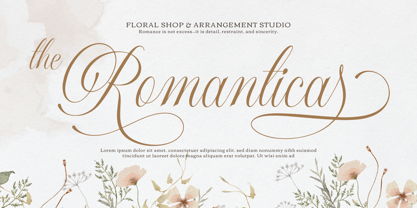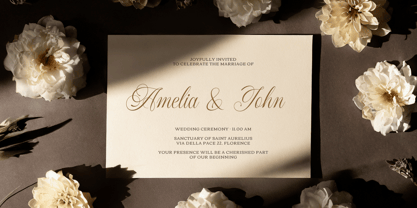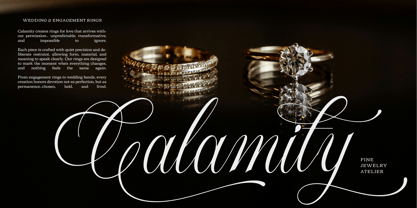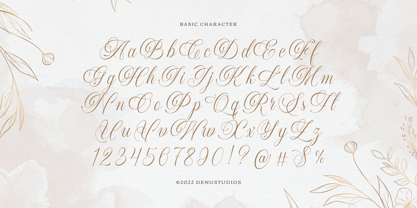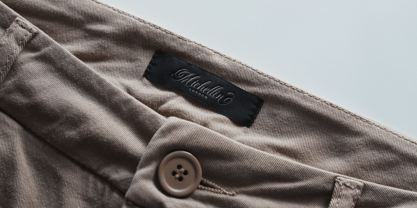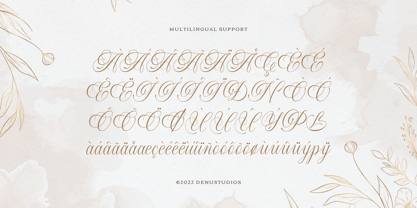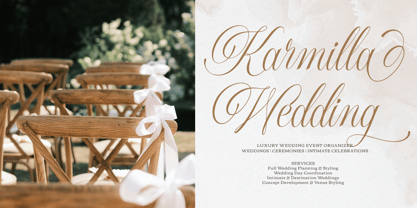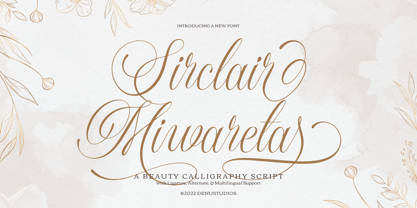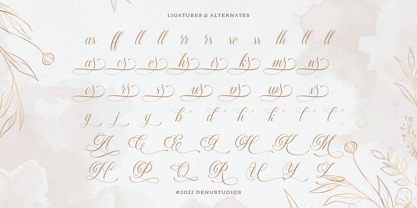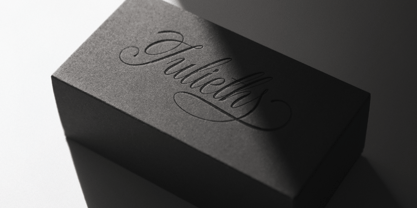
Sirclair Miwareta
La familia tipográfica Sirclair Miwareta fue diseñada por Dede Nugraha y publicada por Denustudio. Sirclair Miwareta contiene 2 estilos y opciones de paquete familiar. Más información sobre esta familia
Sirclair Miwareta | Beauty Callighraphy, from Denustudios, suitable for any projects such as: logos, branding projects, homeware designs, product packaging, mugs, quotes, posters, shopping bags, t-shirts, book covers, name card, invitation cards, greeting cards, label, photography, watermark, special events, and all your other lovely projects that need Callighraphy a taste.